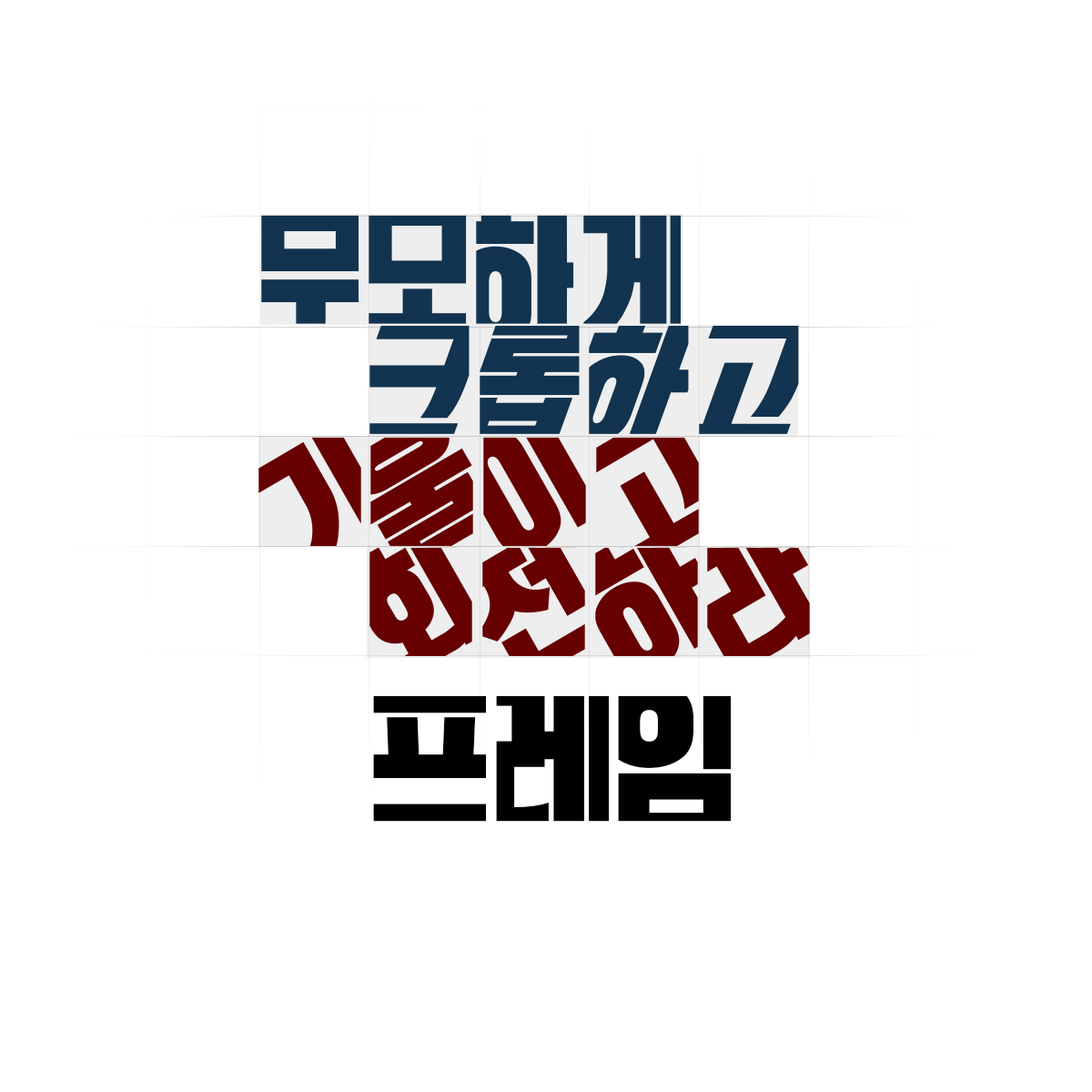
Oblique
Rotate
최소한의 가독성만 남겨두고 최대한 잘라보기도 하고, 기울임, 회전 등의 다양한 연구와 실험을 통해 총 3종으로 탄생하게 되었다. 레트로한 느낌과 단단한 느낌이 공존하여 재미있으면서도 강조적인 문구의 제목용에 잘 어울리는 서체이다.
- Rix프레임 / RixFrame_Pro